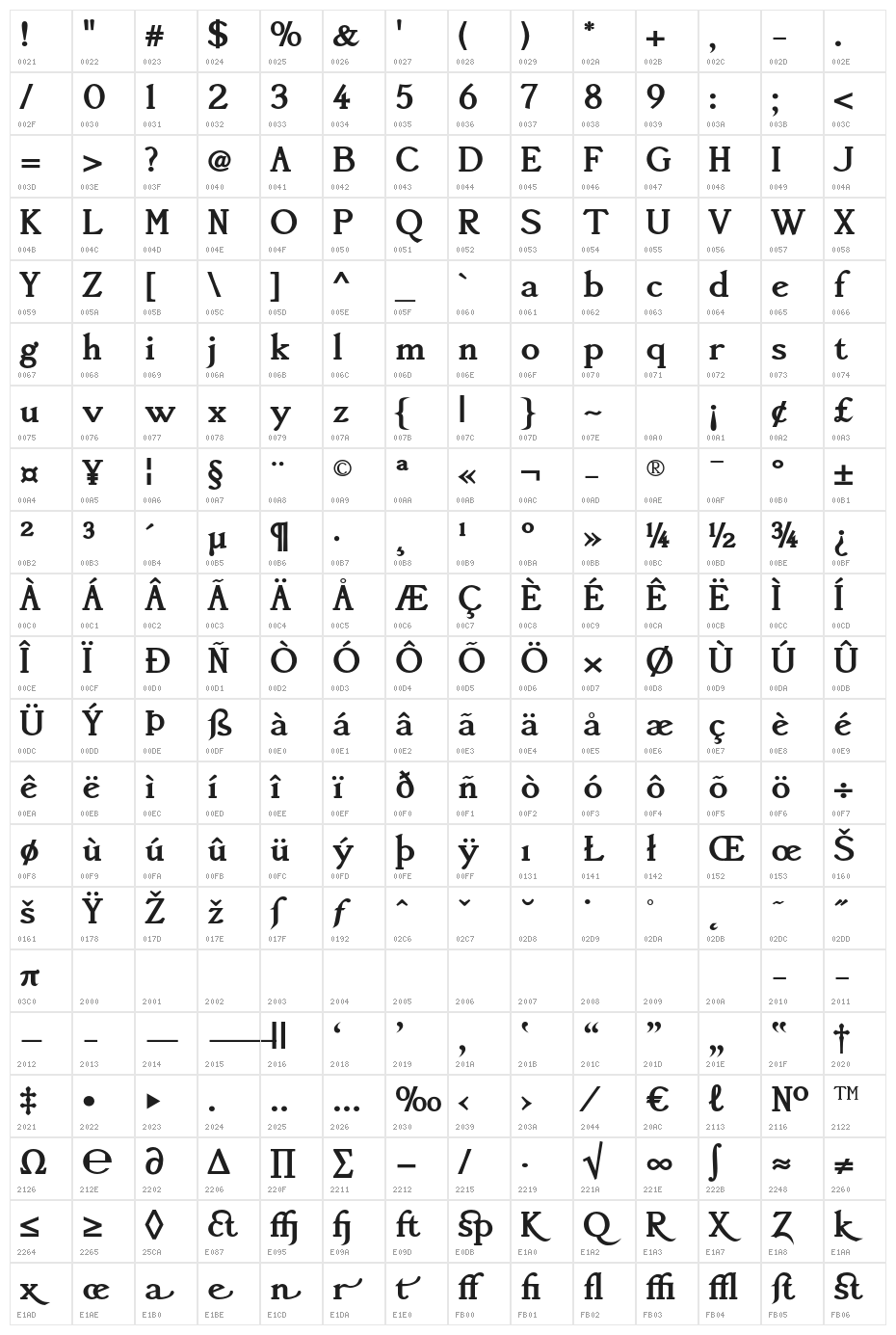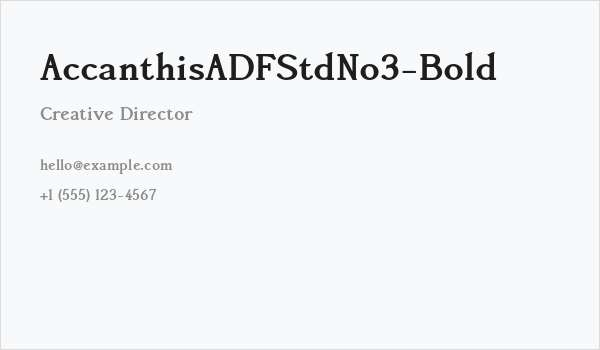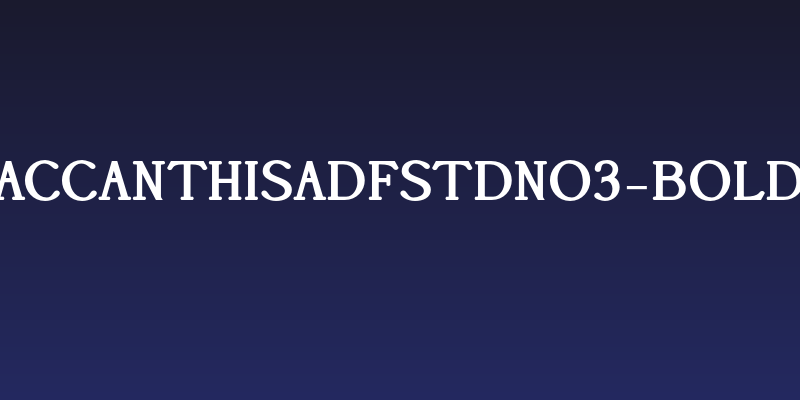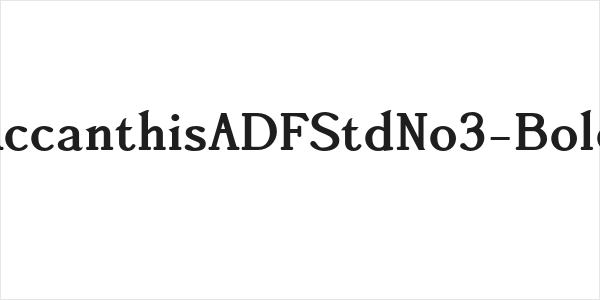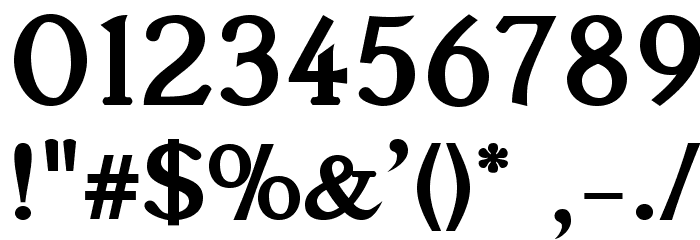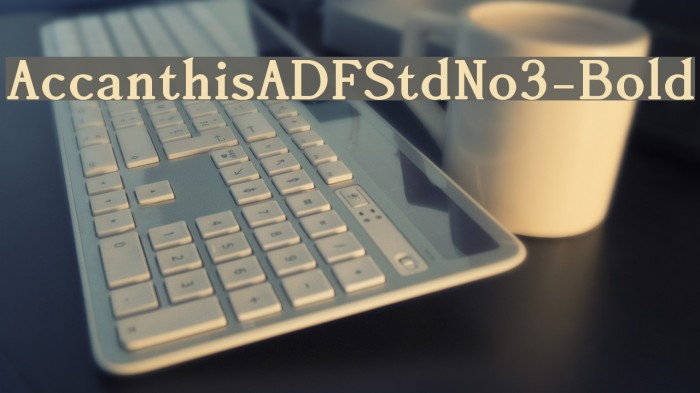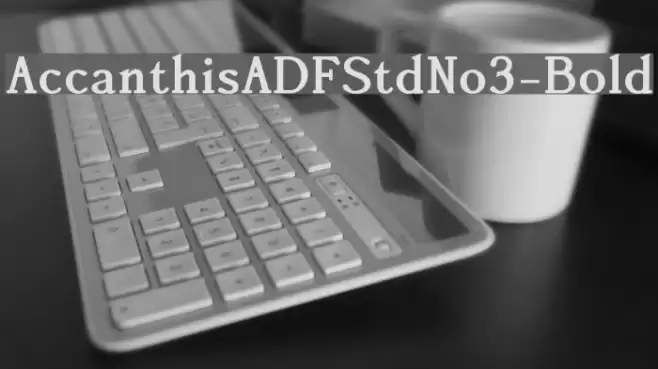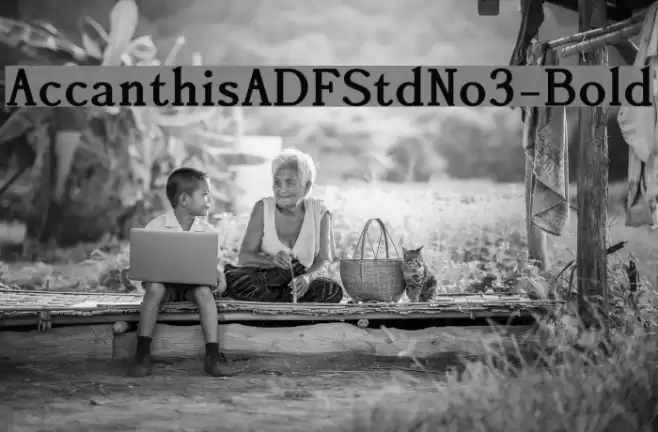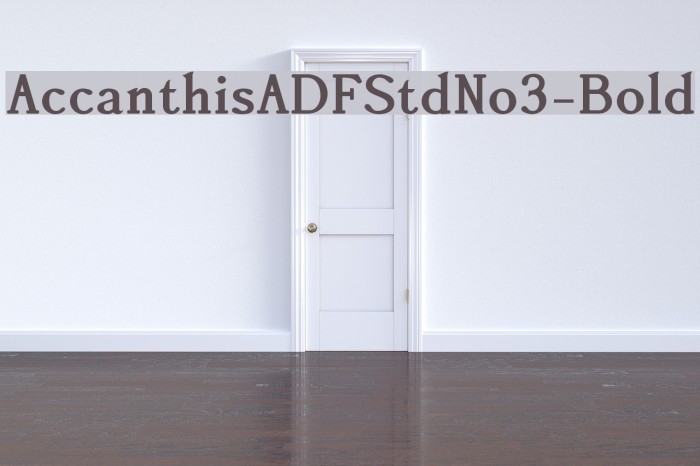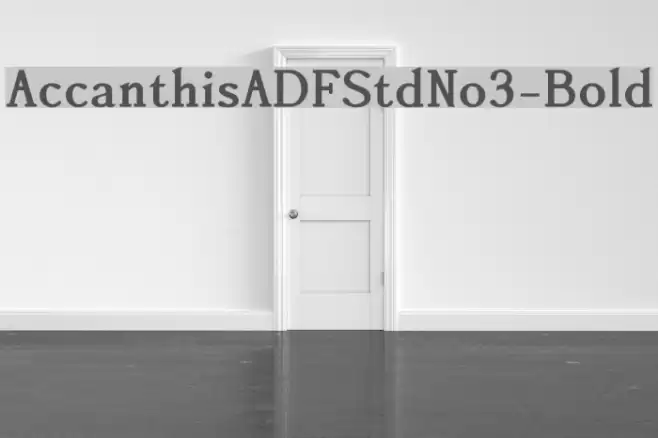
AccanthisADFStdNo3-Bold Font
✎ Serif
| Categorías | Serif |
| Estilo general | Classic |
| Caso de uso | Headlines, Body text, Logos |
| Proyectos propuestos | Ideal for book covers, editorial design, formal invitations, and branding projects that require a touch of sophistication. |